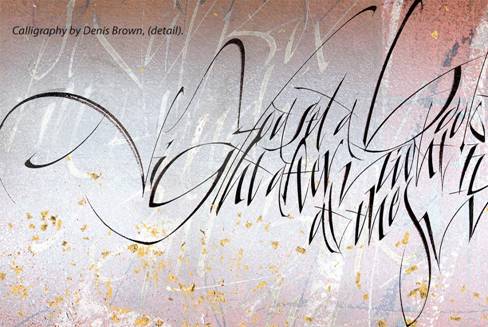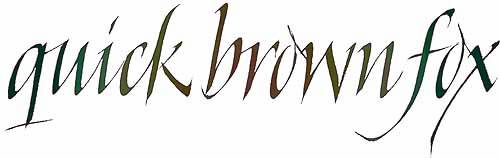
Kalligrafiewochenende "Neuland"
Die Neuland ist ein von Rudolf Koch konzipiertes Alphabet, welches in den letzten Jahren in den USA eine Renaissance erlebte. In diesem Alphabet können Federmanipulationen erlernt, geübt und eingesetzt werden. Das Alphabet eignet sich auch hervorragend zum Stempelschnitt.
Kalligrafiewochenende: Linien in Bewegung
Kalligraphische Bewegungsformen werden erklärt und geübt, aus Formen werden Buchstaben und Wörter. Die Tinte singt Lieder des Lebens aus der Feder ins Papier. Übungen zu „bewegten Formen“ münden in ein freies Alphabet, das innerhalb gängiger Gestaltungsgrundsätze vielfache Möglichkeiten zum Einsatz bietet.
Kalligrafiewochenende: Anglaise und Ornament
Zielgruppe: Kalligrafieinteressierte, die mit der Schwellzugfeder und den Grundlagen der Anglaise vertraut sind
Inhalt: nach einer kurzen Wiederholung der Grundzüge der Anglaise werden die Großbuchstaben dieses Alphabetes vertieft dargestellt. Aus diesen Formen entwickelt sich eine freie ornamentale Gestaltung mit einer fundierten Darstellung des Ornamentes.
Workshop mit Denis Brown:
Rhythm, Flourishing and Polyrhythm
Das Pulsieren des Lebens schlägt im Gleichklang der Jahreszeiten. Jahreszeiten sind bereichert durch Mondzyklen. Wie als Metrum wirkt dabei Tag Nacht Tag.
Grundlage jeder gelungenen Kalligrafie sind Metrum, sind sich überlagende Metren und sind über den Buchstaben hinausgehende Formbereicherungen.
Mit Denis Brown lernen die Teilnehmer diese Gegebenheiten entwickeln.
Bereichert wird der Workshop zusätzlich durch Arbeiten mit Musik und Darstellungen der Formvarianzen der Buchstaben unseres Alphabetes.
Unzialis
Die Unzialis ist die Schrift des keltischen Irland. In ihr dominiert das Formprinzip des Kreises. Diese Schrift eignet sich deshalb auch zum Verlassen der gewohnten linearen Zeilenführung.
Bei der Cancellaresca handelt es sich um ein zeitgemäßes humanistisches Alphabet, das locker, leicht zu schreiben ist, freundlich wirkt und für vielerlei Gelegenheiten und Anlässe einsetzbar ist.